11 ฟอนต์ออกแบบเว็บไซต์ที่จะทำให้เว็บไซต์ของคุณดูใหม่
เผยแพร่แล้ว: 2023-02-02แบบอักษรสำหรับการออกแบบเว็บไซต์ดูเหมือนเป็นส่วนเล็กๆ ของเว็บไซต์ธุรกิจของคุณ แต่ในความเป็นจริงแล้ว แบบอักษรเหล่านี้มีผลกระทบอย่างมากต่อการแปลง
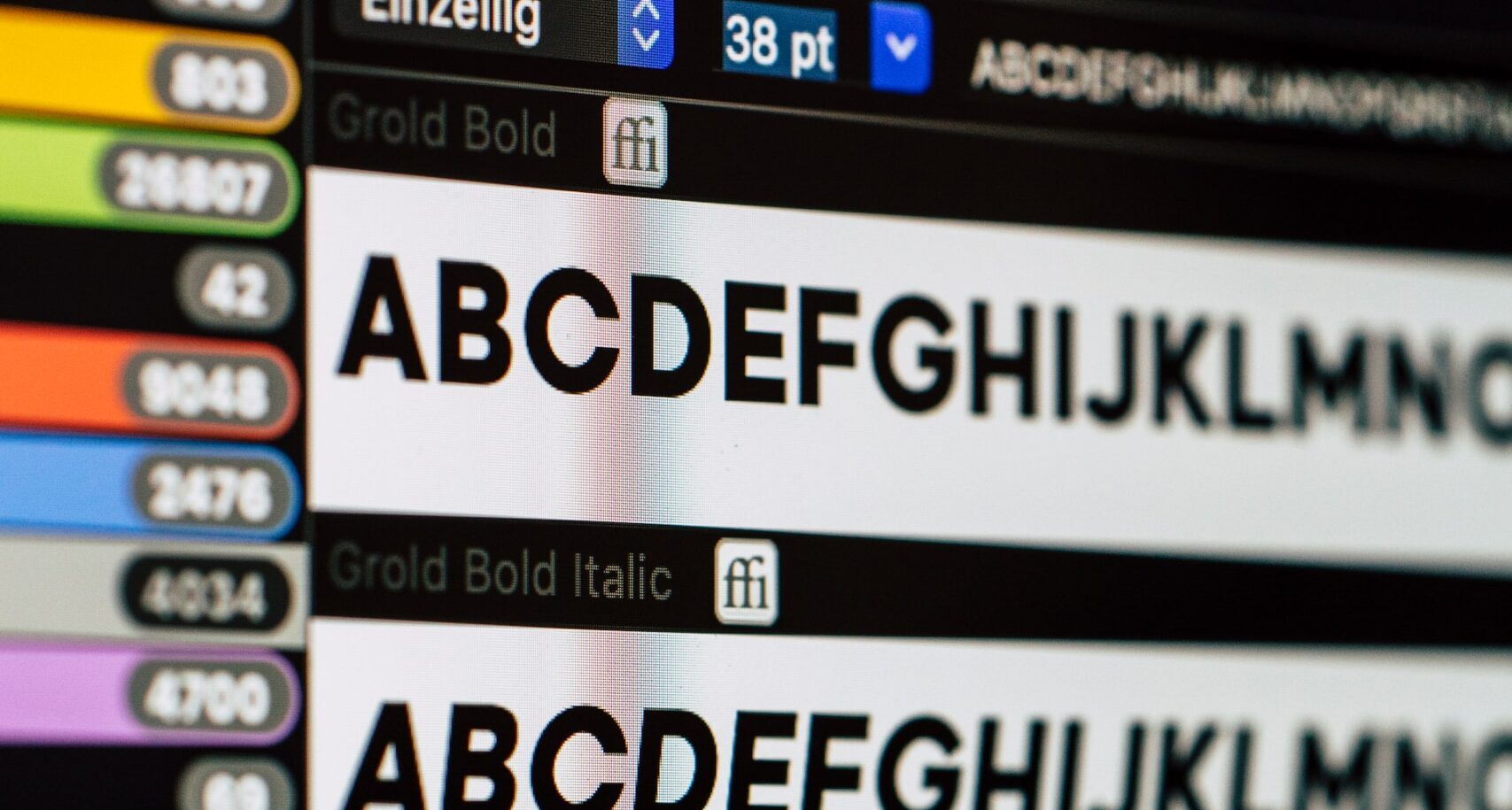
สิ่งที่แยก "สุดยอด" ออกจากสามัญ? เมื่อตัวละครในภาพยนตร์หัวโตสีน้ำเงินตัวหนึ่งอุทานว่า “การนำเสนอ!”
เมื่อออกแบบหน้าเว็บ ลักษณะจะมีบทบาทสำคัญในโครงร่างใหญ่ของสิ่งต่างๆ สมมติว่าคุณอาจมีงานชิ้นหนึ่งที่น่าสนใจซึ่งผู้ชมของคุณน่าจะชื่นชอบ หากงานนำเสนอของคุณดูแย่หรือน่าขยะแขยง คุณอาจผลักผู้ชมคนนั้นออกไป ไกลมาก ๆ.
โชคดีที่ การออกแบบและพัฒนาเว็บไซต์ ไม่ใช่เรื่องยาก คุณต้องทำให้หน้าเว็บของคุณน่าดึงดูด และดึงดูดผู้ชมของคุณให้เข้ามา นั่นเป็นวิธีที่คุณสร้างประสบการณ์ที่ยอดเยี่ยมให้กับผู้ใช้ของคุณ โดยเฉพาะอย่างยิ่ง การเลือกแบบอักษรของคุณอาจส่งผลต่อการที่ผู้อ่านจะอยู่หรือออกจากหน้าเว็บของคุณ
อย่าลังเลที่จะใช้ฟอนต์เหล่านี้สำหรับการออกแบบหน้าเว็บของคุณ และเข้าถึงศักยภาพสูงสุดของคุณ หวังว่าคุณจะได้รับแนวคิดทั่วไปว่าควรเลือกแบบอักษรใดและเหตุใดจึงมีประสิทธิภาพสำหรับการเข้าถึงทางออนไลน์
วิธีเลือกแบบอักษรสำหรับออกแบบเว็บ
หน้าเว็บของคุณมีรูปลักษณ์ที่ชัดเจนและไม่เหมือนใคร วิธีแสดงข้อความในรูปลักษณ์นั้นเป็นกุญแจสู่ความสำเร็จของคุณ อย่างไรก็ตาม โปรดจำไว้ว่าคุณสามารถปรับปรุงความสำเร็จนั้นได้โดยพิจารณาจากปัจจัยทั้งหกเหล่านี้:
- ความชัดเจนและอ่านง่าย
- ความสอดคล้องของแบรนด์
- มู้ดแอนด์โทน
- หลักเกณฑ์การเข้าถึงเว็บ
- ความเข้ากันได้ข้ามเบราว์เซอร์
- ความสามารถในการปรับขนาด
1. ความชัดเจนและอ่านง่าย
ความชัดเจนคือความง่ายที่ผู้ใช้ของคุณสามารถแยกแยะความแตกต่างระหว่างอักขระต่างๆ หากเครื่องอ่านของคุณมีปัญหาในการระบุว่าตัวอักษรเป็น "S" ของ "5" หรือไม่ คุณอาจต้องเลือกแบบอักษรอื่น แบบอักษรบางตัวมีรูปร่างที่แตกต่างกันสำหรับอักขระที่คล้ายกัน (เช่น "1" ตัวพิมพ์ใหญ่ "I" และตัวพิมพ์เล็ก "l") เพื่อแยกความแตกต่างออกจากกัน
ความชัดเจนอาจได้รับอิทธิพลจากปัจจัยอื่นๆ เช่น ตัวเลือกสีพื้นหน้าและพื้นหลัง ขนาดฟอนต์ และน้ำหนักฟอนต์ ตัวอย่างเช่น ตัวอักษรบางตัวอาจอ่านง่ายขึ้นเมื่อคุณเพิ่มขนาดแบบอักษร แต่จะอ่านได้หรือไม่
ในเรื่องนั้น ความชัดเจนแตกต่างจากการอ่านง่าย
ความสามารถในการอ่านคือความสะดวกสบายของผู้อ่านในการอ่านบล็อกข้อความ ความสบายในระดับนั้นยังได้รับอิทธิพลจากความชัดเจนของข้อความด้วย ถ้าคำเล็กเกินไปที่จะแยกแยะตัวอักษรออกจากกัน คำนั้นอาจไม่สามารถอ่านได้ นี่เป็นกรณีในบล็อก "การพิมพ์ที่ดี" ทางกฎหมายที่หนาแน่นซึ่งใคร ๆ ก็สามารถอ่านข้อความทั้งหมดได้ แต่ไม่สะดวกเท่าที่พวกเขาต้องการ
2. ความสม่ำเสมอของแบรนด์
คุณต้องทำให้การนำเสนอของคุณสอดคล้องกัน ในขณะที่เสียงของแบรนด์ของคุณเป็นรากฐานที่แข็งแกร่งสำหรับหน้าเว็บของคุณ การรักษาเอกลักษณ์เดิมไว้ตลอดนั้นเป็นตัวกำหนดว่าคุณจริงจังแค่ไหนในการผลักดันประเด็นของคุณ งานนำเสนอของคุณมุ่งเป้าไปที่การบอกเล่าเรื่องราวเฉพาะ และคุณกำลังเชิญชวนให้ลูกค้าระบุและรับทราบเรื่องราวนั้น
ค้นหาแบบอักษรที่ทำให้การเล่าเรื่องเข้าที่ หากคุณกำลังมองหาโทนสีแบบมืออาชีพ ให้ใช้ฟอนต์ที่ดูเป็นมืออาชีพ สำหรับเนื้อหาที่น่าสนใจและเป็นมิตร ให้ใช้แบบอักษรที่ดูสบายตา คุณสามารถค้นหาอันที่เหมาะกับใบเสร็จได้หากคุณตั้งใจพอ
3. มู้ดแอนด์โทน
จิตวิทยาฟอนต์คือการศึกษาว่าฟอนต์ส่งผลต่อการรับรู้เนื้อหาของคุณอย่างไร ฟอนต์บางตัวถูกนำมาใช้เพื่อจุดประสงค์เฉพาะ และผู้คนก็คุ้นเคยกับมัน ฟอนต์อื่นๆ เพียงแค่กระตุ้นความคิดและอารมณ์บางอย่างจากผู้อ่าน ไม่ว่าในกรณีใด คุณอาจต้องการใช้แบบอักษรที่ช่วยให้ผู้อ่านเข้าถึงอารมณ์ที่คุณต้องการสร้าง
คุณสามารถเล่นกับแบบอักษรเพื่อสร้างอารมณ์นั้น ตัวอย่างเช่น แบบอักษรบางตัวมีประสิทธิภาพสำหรับส่วนหัวมากกว่าที่เป็นข้อความเนื้อหา การผสมและจับคู่แบบอักษรสามารถสร้างความรู้สึกที่น่าทึ่งให้กับเนื้อหาของคุณ และดึงอารมณ์ที่ทรงพลังออกมา
4. หลักเกณฑ์การเข้าถึงเว็บ
เว็บไซต์ของคุณจะต้องรวมผู้เข้าชมทั้งหมด ทำให้มั่นใจได้ว่าผู้ที่ประสบปัญหาหรือข้อจำกัดจะยังคงยินดีต้อนรับเข้าสู่เว็บไซต์ของคุณในลักษณะเดียวกับคนอื่นๆ ไม่ใช่แค่เครื่องมือในการสร้างการเข้าชมธุรกิจของคุณมากขึ้นเท่านั้น แต่ยังส่งเสริมชุมชนในหมู่ผู้บริโภคทั้งหมดของคุณด้วย
ในการทำเช่นนี้ นักออกแบบมักจะใช้หลักเกณฑ์ในการปรับปรุงการเข้าถึงเว็บไปยังไซต์ของตน กฎและหลักเกณฑ์เหล่านี้ทำให้เนื้อหาเป็นมิตรกับผู้ใช้มากขึ้นและเข้าใจง่ายสำหรับผู้เยี่ยมชมทุกคน แม้ว่าจะไม่จำเป็นในเวลานี้ แต่การปรับปรุงการเข้าถึงเว็บเป็นวิธีที่ดีในการสร้างสายสัมพันธ์กับฐานผู้บริโภคของคุณ และแสดงให้พวกเขาเห็นว่าคุณห่วงใยและต้องการให้พวกเขาเป็นส่วนหนึ่งของสิ่งที่คุณกำลังสร้าง สี่มาตรฐานหลักคือ:
- รับรู้ได้ พูดง่ายๆ ก็คือ ผู้บริโภคของคุณจะต้องเข้าใจเนื้อหาของคุณ นอกจากนี้ยังไม่จำกัดเพียงการ "เห็น" เนื้อหาเท่านั้น โปรดทราบว่าผู้ใช้ที่ตาบอดหรือมีสายตาเลือนรางให้ใช้ซอฟต์แวร์ตัวอ่านหน้าจอทางเลือกเพื่อช่วยนำทางอินเทอร์เน็ต พิจารณาผู้ใช้เหล่านี้เมื่อคุณตั้งค่าหน้าเว็บของคุณ
- ใช้งานได้ ซึ่งหมายความว่าผู้ใช้ทุกคนสามารถเข้าถึงและใช้งานทุกส่วนของหน้าเว็บของคุณได้ (ข้อความ ลิงก์ เสียง วิดีโอ สื่ออื่นๆ) โดยทั่วไป เว็บไซต์ที่ใช้งานได้ส่วนใหญ่จะเรียบง่าย ดังนั้นจึงนำทางได้ง่าย
- เข้าใจได้ ผู้ใช้ของคุณจะต้องสามารถแยกแยะข้อมูลทั้งหมดที่คุณพูดได้ คุณสามารถใช้ภาษาทั่วไปหรือเสนอภาษาอื่น ในทำนองเดียวกัน การนำทางเว็บไซต์ของคุณต้องได้รับการจัดระเบียบอย่างเป็นธรรมชาติและเป็นธรรมชาติ เพื่อช่วยให้ผู้ใช้เข้าใจคุณและผลิตภัณฑ์ของคุณ
- แข็งแกร่ง เนื้อหาบนเว็บไซต์ของคุณควรแยกย่อยและแยกวิเคราะห์ได้ง่ายโดยโปรแกรมช่วยเหลือ เช่น โปรแกรมอ่านหน้าจอ ด้วยวิธีนี้ ผู้ที่ประสบปัญหาจะยังคงเป็นส่วนหนึ่งของประสบการณ์ที่เว็บไซต์ของคุณมอบให้
- อย่ากลัวที่จะทดลอง นั่นคือสิ่งที่กระบวนการออกแบบมีไว้สำหรับ คุณควรสำรวจว่าอะไรได้ผลและอะไรไม่ได้ผล